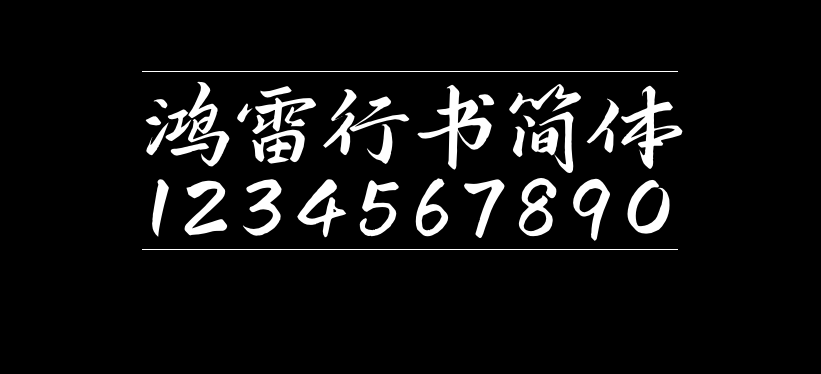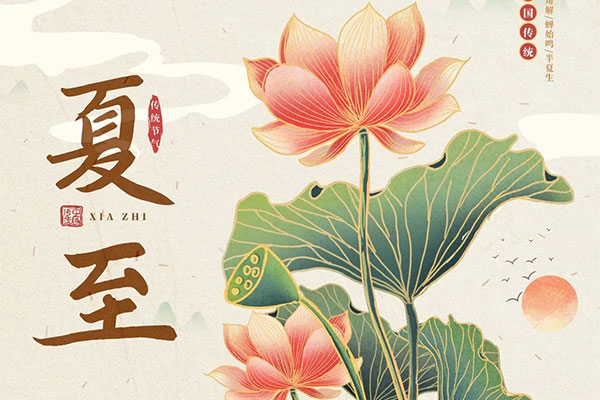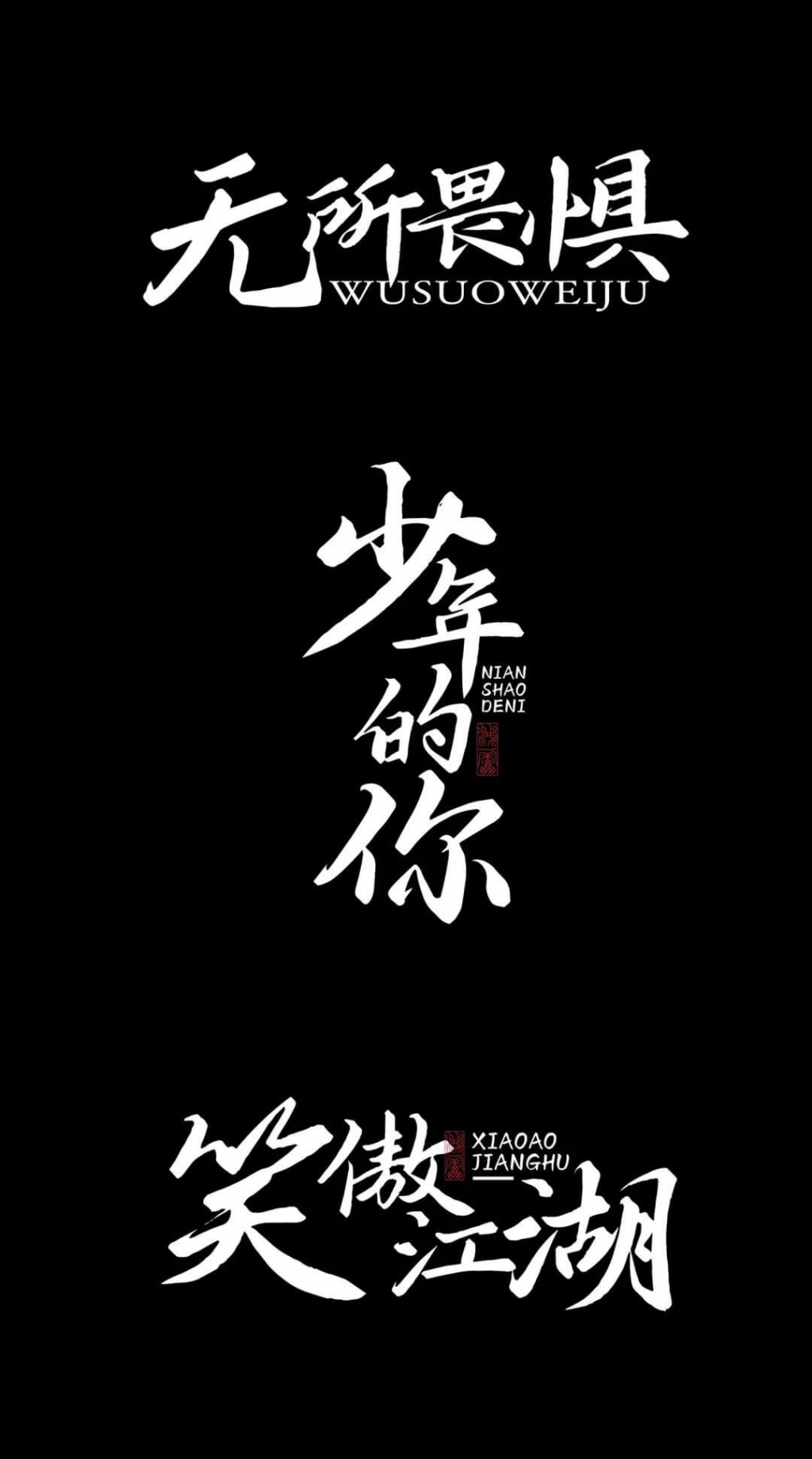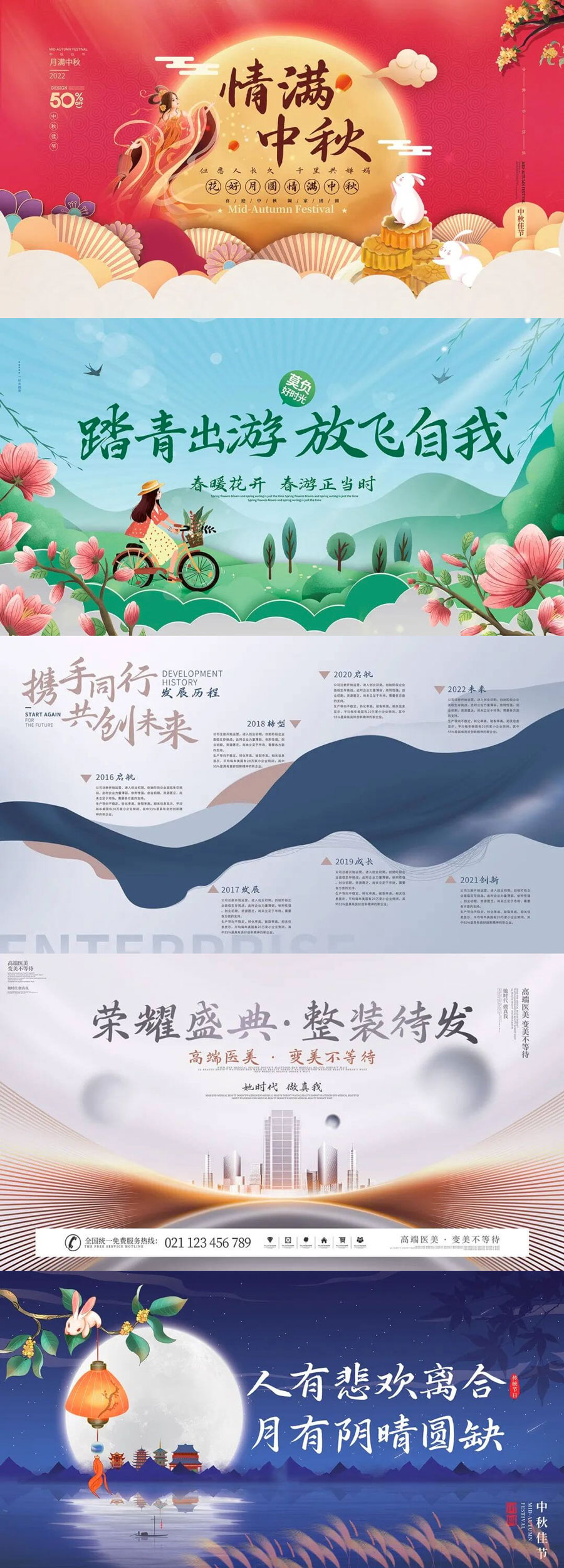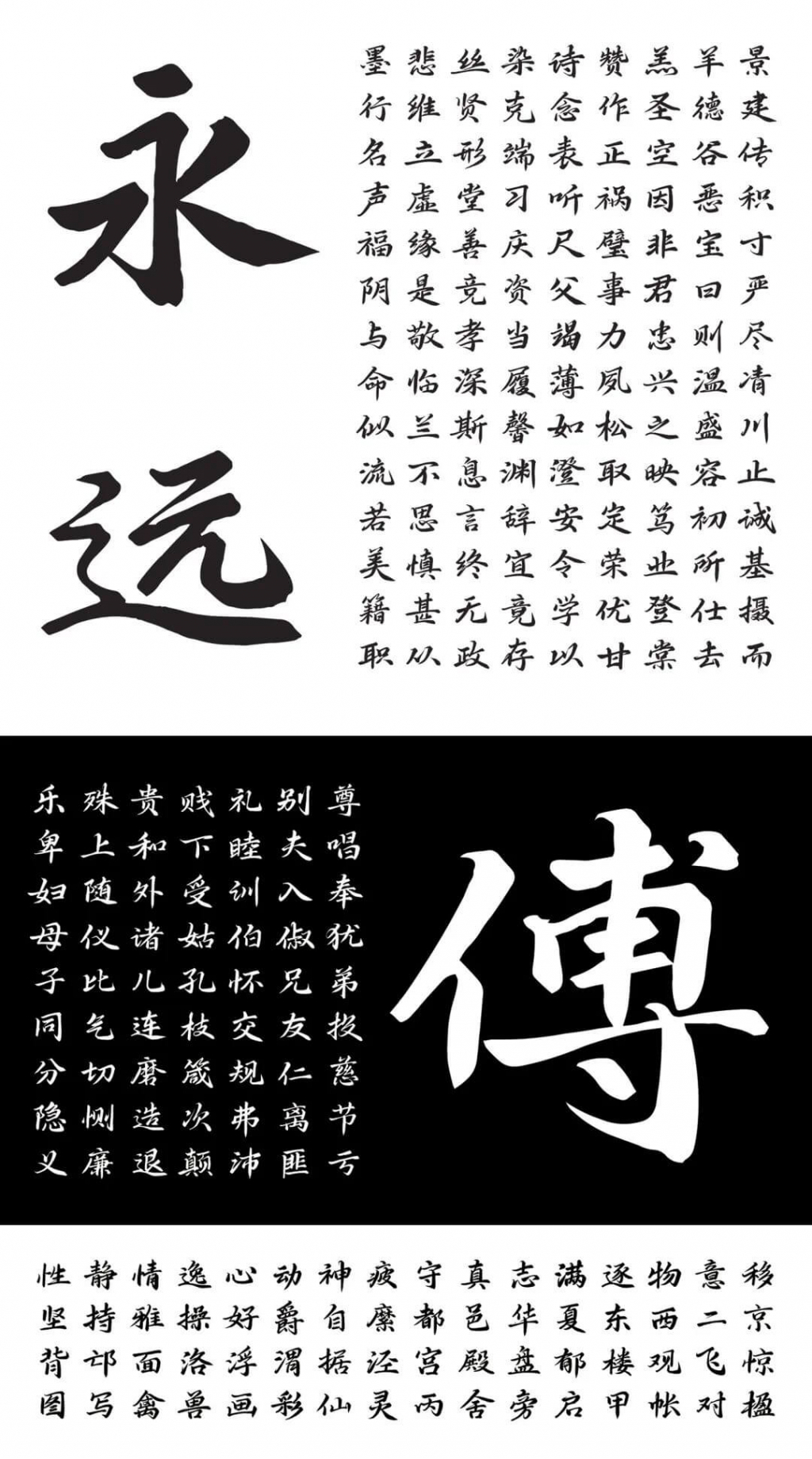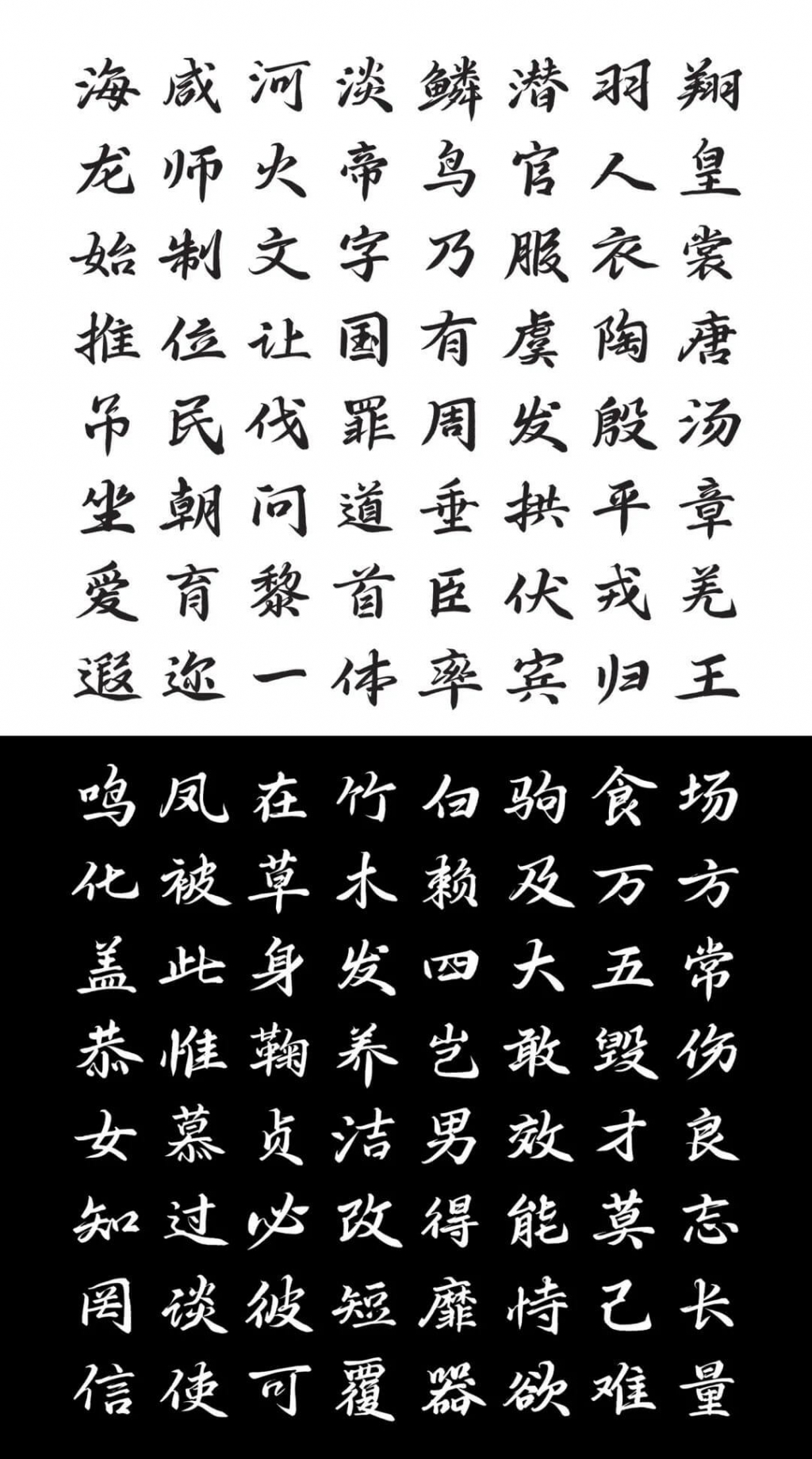
鸿雷行书简体
鸿雷行书简体是国内知名字体设计师殷鸿雷创作推出的第二款免费商用书法字体。前面自由君分享过该作者的第一款免费字体:《鸿雷板书简体》。
鸿雷行书简体字体笔锋流畅行云流水,字形舒展有型。该字体依旧全渠道免费商用,感谢作者的分享。
以下是对作者发布字体的原文引用:
还记得2020年4月份我发布了《鸿雷板书简体》,不知道有多少人使用过呢?
时隔两年越发觉得那个字体好丑啊,于是通过两年的时间,想看看自己的字迹有没有进步,于是无聊的我两年后再次书写了一套个人免费商用的手写字体《鸿雷行书简体》。
然而,一款新字体的出现,对于设计师来说最关心的问题无非就两个:
1、字体质量。
关于质量,下面案例大家就自己看了,吹再多都不如自己下载使用看看,反正免费,不用白不用是吧。
对于这套的字体的介绍这里就不吹嘘了
设计师们自己看看
鸿雷行书简体鸿雷行书简体
鸿雷行书简体